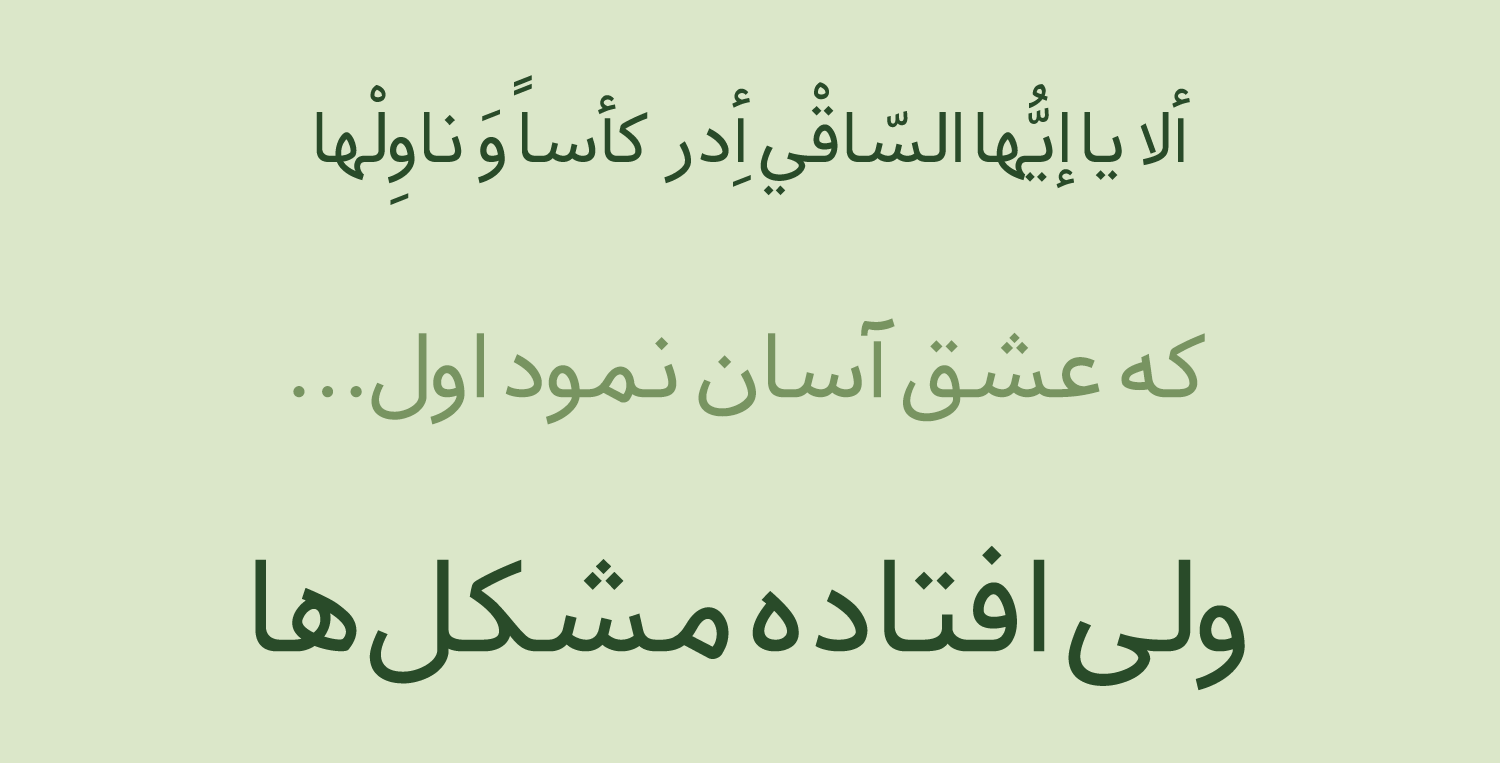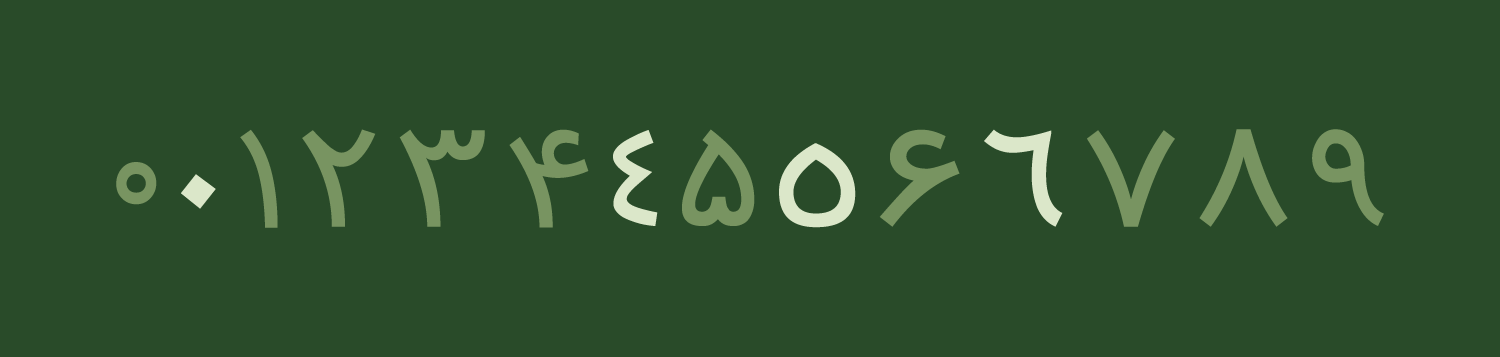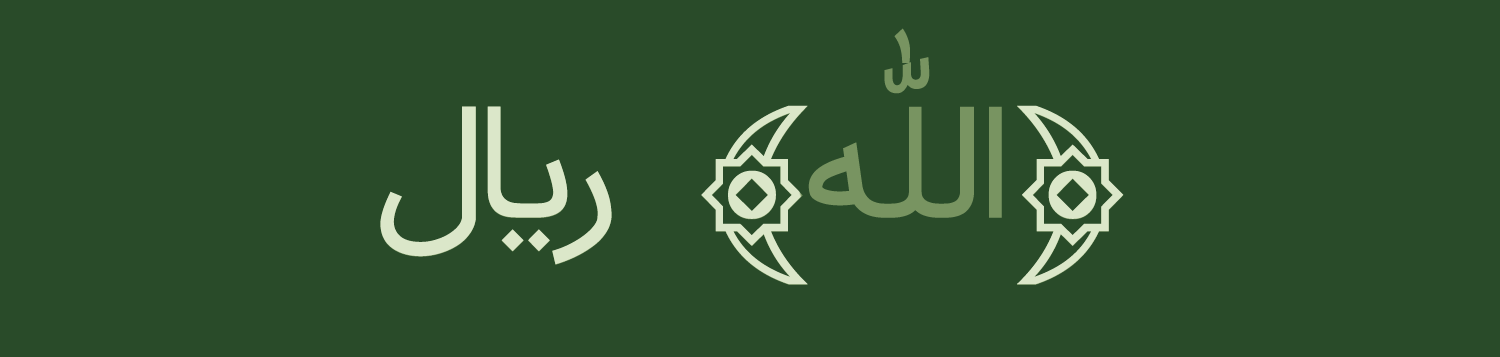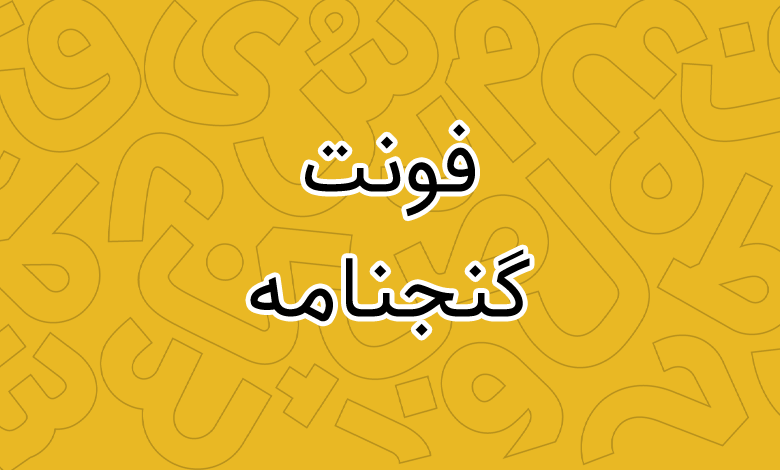
فونت گنجنامه (GanjNameh)
فونت گنجنامه (به انگلیسی: GanjNameh) یکی از فونتهای رایگان و آزاد است که چند سالی از انتشار آن میگذرد. این فونت که به سبک خط سنس طراحی شده برای استفاده در متون بلند مناسب است و از نظر ظاهری دارای ساختاری است که خوانایی بالایی را به متون بلند میدهد.
فونت گنجنامه توسط صالح سوزنچی طراحی و توسعه داده شده است که در کارنامه کاری خود چندین فونت آزاد را دارا میباشد. این قلم از وزن معمولی Regular پشتیبانی کرده و دارای ظاهری استخوانی اما در عینحال نرم و لطیف است که هنگام استفاده در متن سیاه بهنظر میرسد.
پیش از شروع بد نیست بدانید که نام این فونت برگرفته از یک منطقه گردشگری در شهر همدان گرفته شده است که دو سنگنوشته به سبک خط میخی در کوهپایههای کوه الوند همدان قرار دارند و همهروزه پذیرای بازدیدکنندگان از شهرها و کشورهای مختلف جهان هستند. در این ناحیه یک آبشار بلند نیز وجود دارد که در هر فصل از سال رنگ و بوی تازهای دارد.
سبک طراحی و وزن فونت گنجنامه
فونت گنجنامه با سبک خط سنس طراحی شده است که اینگونه خطوط دارای ساختاری نرم و دوستانه برخلاف خط نسخ هستند. این قلم رایگان از یک وزن معمولی Regular پشتیبانی میکند که میتوانید از آن درون متنهای بلند یا کوتاه استفاده کنید. هر چند که استفاده از آن برای عناوین توصیه نمیشود. چرا که فونت با وزن ضخیمتر برای عناوین و تیترها انتخاب بسیار بهتری است.
پشتیبانی از زبان فارسی و عربی
فونت گنجنامه از آنجایی که یک پروژه آزاد و متنباز است، در همان نسخههای اولیه طراح کار خود را با تمرکز بر روی دو زبان فارسی و عربی آغاز نمود. اما متاسفانه چند سالی است که توسعه و آپدیت این فونت متوقت شده و خبری از پشتیبانی زبانهای لاتین یا سایر زبانهای خاورمیانهای نیست.
تمامی حروف و کاراکترها در فونت گنجنامه برای هر زبان دارای گلیف اختصاصی خود هستند. حروفی که مشترک برای فارسی و عربی هستند یکسان بوده، اما حروفی نظیر «ک، ی، ه، ؤ، ئ» در عربی که متفاوت از نسخه فارسی هستند دارای گلیف جداگانه خود هستند که با تغییر زبان صفحه کلید به عربی امکان تایپ آنها را دارید.
این فونت از اعراب به شکل درست و استانداردی پشتیبانی میکند. کلیه اعراب اصلی و تنوینها در همنشینی مناسبی در کنار سایر اعراب «همزه، سکون و تشدید» قرار میگیرند که باعث بههم ریختگی متن یا چسبیدن برخی اعراب به حروف قبل یا بعد نمیگردد.
پشتیبانی استاندارد از اعداد فارسی و عربی
اعداد فونت گنجنامه بر اساس استاندارد گلیفهای یونیکد طراحی شدهاند. در زبان عربی اعداد «۰۴۵۶» متفاوت از نسخه فارسی «۰۴۵۶» تایپ میشوند که همانطور که در تصویر زیر هم میبینید این حالت با رنگ متفاوت مشخص شده است.
در صورت تنظیم زبان صفحه کلید روی عربی اعداد متفاوت با شکل استاندارد عربی تایپ خواهند شد. در غیر این صورت برای زبان فارسی نیز اعداد همان زبان تایپ میگردد. دقت کنید عدد صفر دارای دو حالت است که در فارسی به صورت تو خالی اما در عربی به شکل نقطه تایپ میشود.
این فونت بر خلاف بیشتر فونتهای دیگر به دلیل متوقف شدن پروژه، فاقد نسخه مخصوص با اعداد فارسی هک شده است.
دارای گلیف های خاص
در این قلم چند کاراکتر و گلیف خاص هم به چشم میخورد. یکی کلمه «الله» و دیگری «ریال» که در صورت تایپ این دو کلمه با استفاده از کلیدهای میانبر صفحه کلید که دارای عدد یونیکد مختص به خود هستند، به صورت یک کاراکتر تایپ خواهد شد.
این گلیفها متفاوت از نسخهی تایپ شده این کلمات هستند و روی هم رفته یک گلیف واحد را تشکیل میدهند.
مناسب برای موبایل و اپلیکیشن
میتوانید به طور کلی این فونت را به عنوان فونت اصلی سایت خود قرار داده یا اینکه از یک فونت ضخیم همچون فونت ساحل یا نسخههای ضخیم فونت ایران سنس و ایران یکان برای فونت عناوین و تیترها استفاده کرده و فونت گنجنامه را برای فونت متون بلند در سایت خود انتخاب کنید که ظاهری شیک هم به سایت شما خواهد داد.